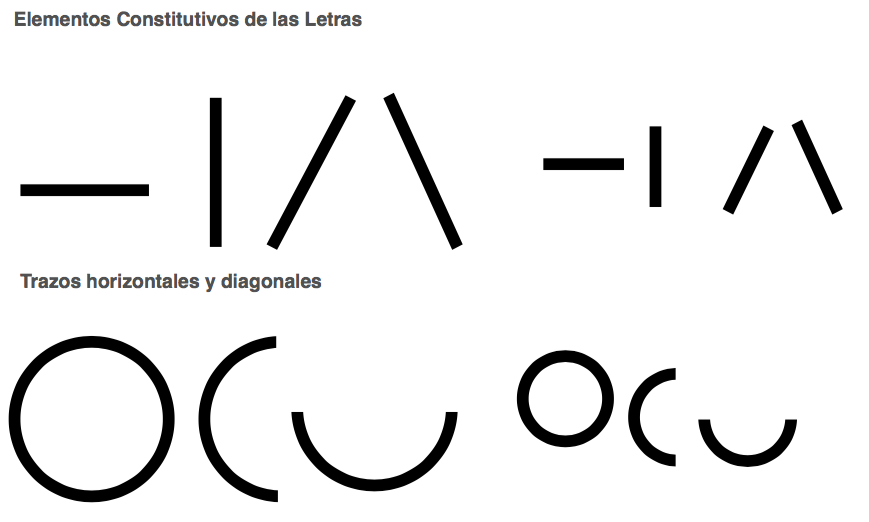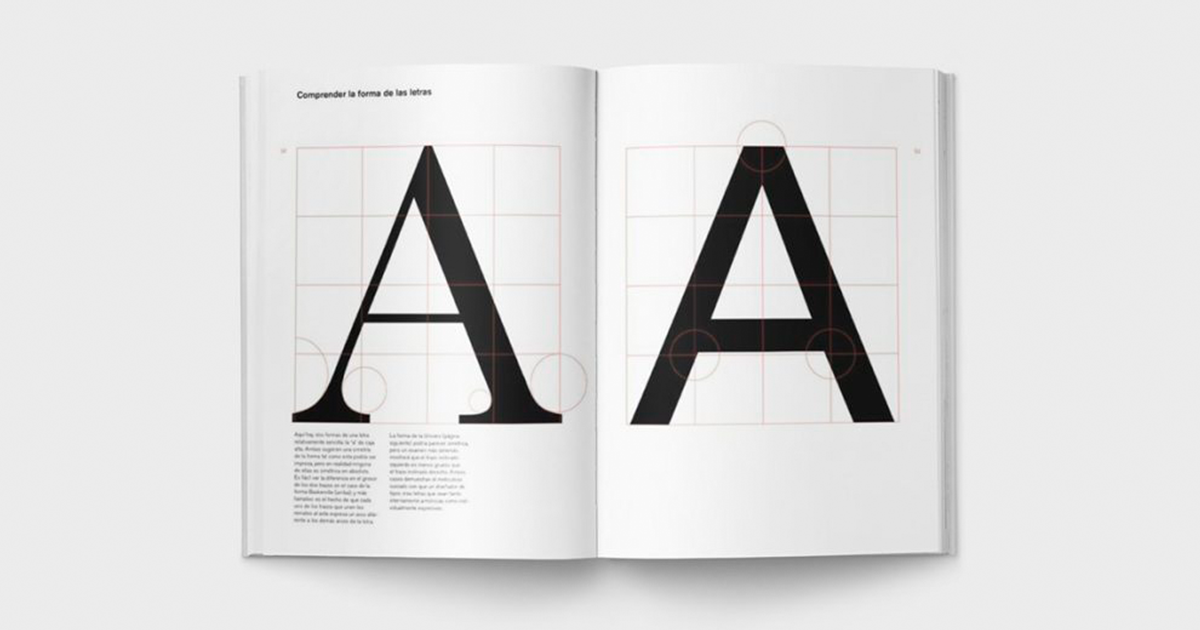
Descarga gratis un manual de principios básicos de tipografía
El diseño busca comunicar y algo que resulta elemental para ello es la combinación de estética y funcionalidad en la tipografía. Diseñar tipografías es diseñar un conjunto de letras, números y signos que tienen características comunes, que se han creado bajo un mismo estilo, son familias de caracteres cuyos miembros comparten diseños comunes, pero que pueden variar en peso y estilos.
Para conocer, entender y visualizar de manera clara los atributos y características de la tipografía, BlueTypo (@bluetypo), estudio de diseño especializado en el desarrollo de tipografía, cartel, diseño e interacción, comparte con Domestika un manual con conceptos básicos para conocer lo esencial de la tipografía.
Como dijo la diseñadora gráfica Paula Scher, "La tipografía es pintar con palabras"; la tipografía es a la palabra escrita, lo que el tono de voz es cuando hablamos: crean atmósfera, estilo, reflejan o inducen estados anímicos, contribuyen activamente en la comunicación.
Cuenta con una dialecto técnico muy amplio para estandarizar las partes de las letras, sus trazos, proporciones y la composición de los textos. Es complicado abarcar semejante glosario, pero sí es importante conocer los principios básicos.